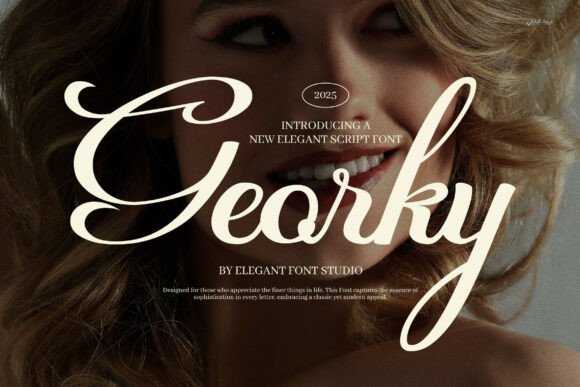
Georky Wedding Script
إذا كنت تبحث عن أصول عالية الجودة مثل Georky Wedding Script، فإن هذه الحزمة المميزة هي خيار رائع لمشاريعك الإبداعية.
سواء كنت تقوم بإنشاء منتجات الطباعة عند الطلب أو دعوات الزفاف أو رسومات وسائل التواصل الاجتماعي، فإن Georky Wedding Script هو الخيار المثالي.